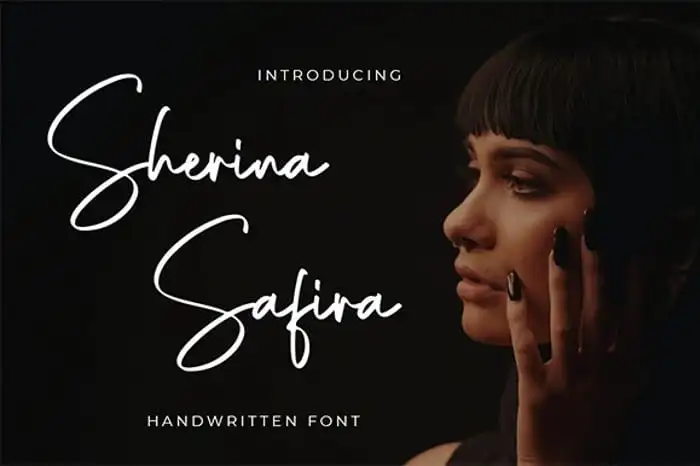
Sherina Safira Handwritten Font – Download Grátis
A fonte Sherina Safira Handwritten é uma escolha perfeita para aqueles que procuram adicionar um toque delicado a seus designs. Feito pela estúdio font-designer Bluestype Studio, essa font script surpreendentemente bela transformará qualquer conceito em um verdadeiro destaque. Com seu traçado feminino e encantador, Sherina Safira é ideal para decorar textos de modo elegante e romântico. Não importa o uso que você dê a esta fonte, ela certamente fará sua marca: seja no nome de um produto, nas etiquetas de uma camiseta ou na dedicatória de um livro. É uma escolha perfeita para quem busca dar um toque suave e delicado aos seus projetos design. Sherina Safira se destaca como a fonte ideal para aqueles que buscam um contraponto sofisticado à natureza do seu design, criando um equilíbrio entre força e feminilidade. Em uma época em que os designs digitais estão cada vez mais presentes na vida diária, uma fonte com o charme de Sherina Safira é certamente um complemento inigualável para seus projetos.